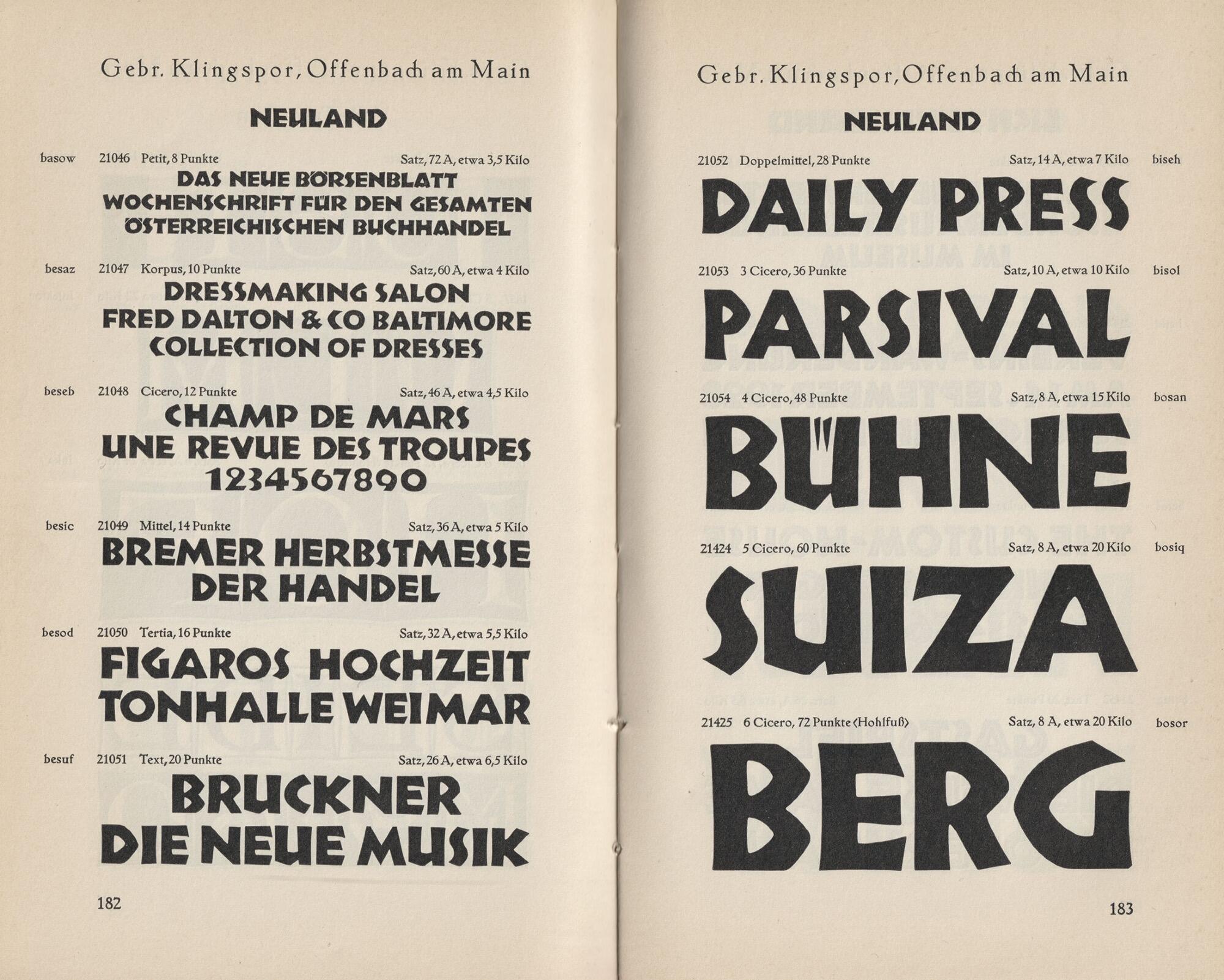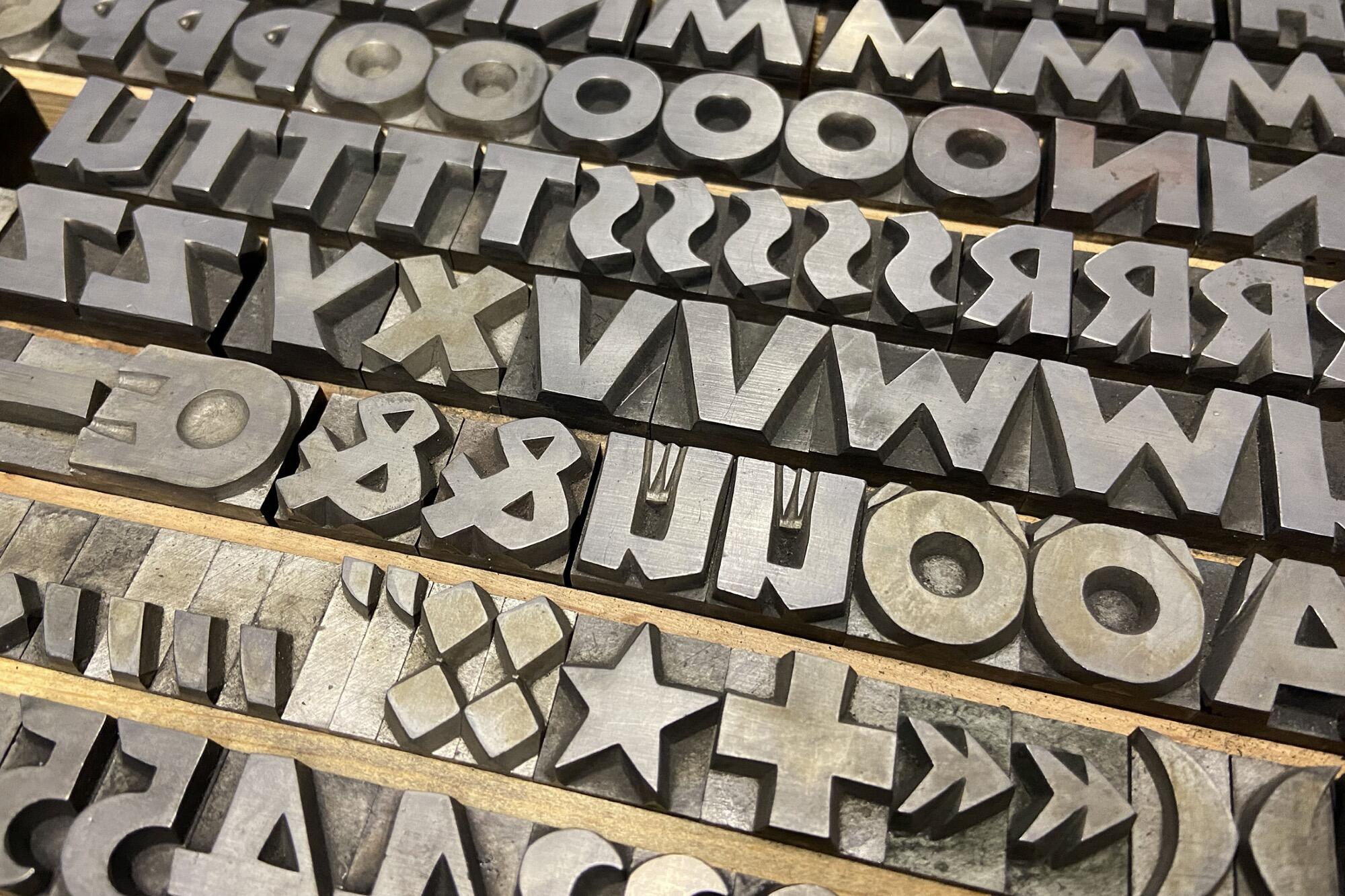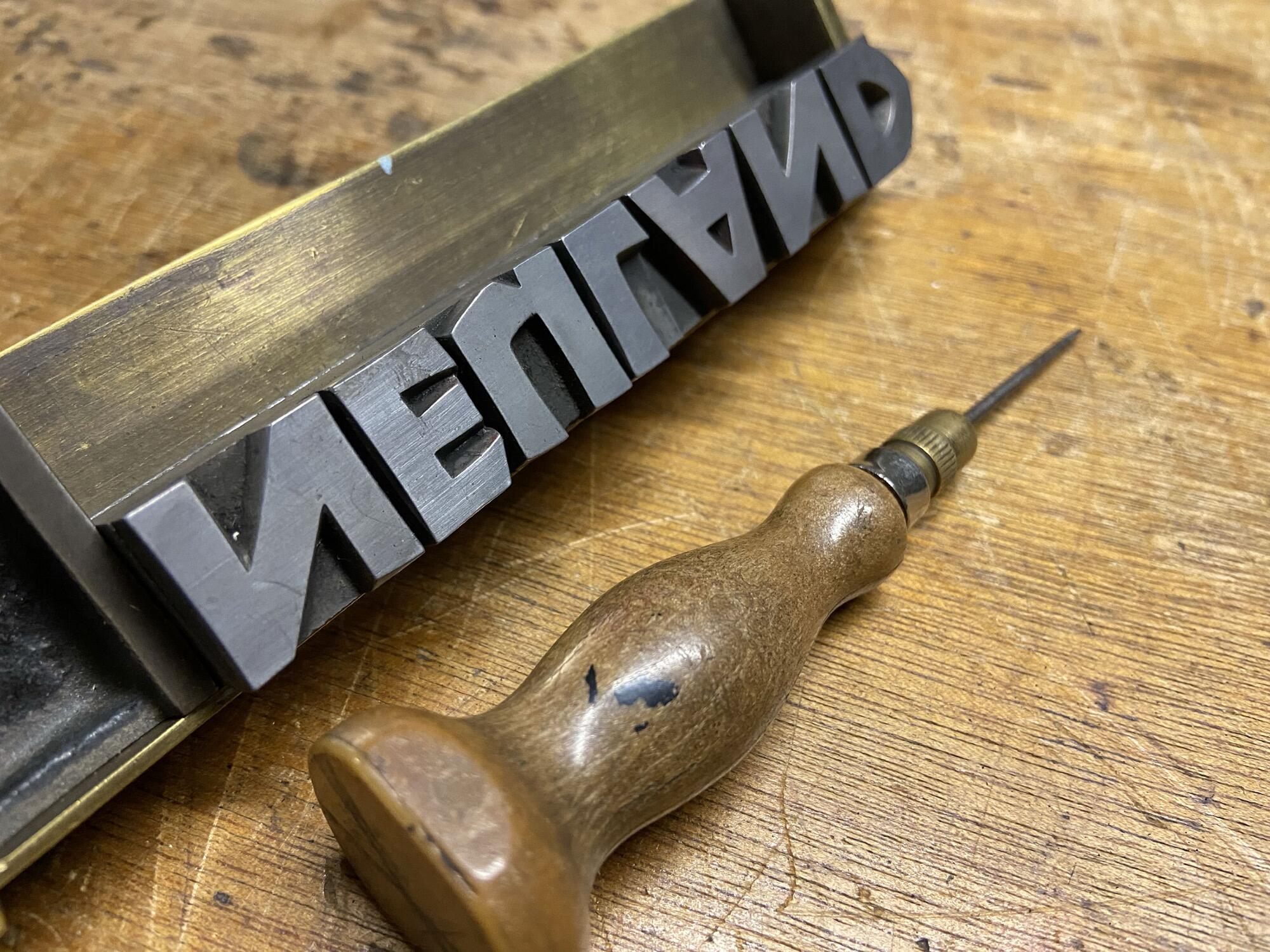
Die Versal-Schrift Neuland von Rudolf Koch erschien 1923 bei den Gebrüdern Klingspor in Offenbach. Obwohl eigentlich eher als Schreibmeister bekannt, versuchte sich Koch bei der Neuland selbst als Stempelschneider. Er wollte eine Schrift schaffen, die direkt aus dem Werkstoff entsteht und nicht durch Nachempfinden einer vorgegebenen Zeichnung.
»Daß ich eine Schrift selbst in Messing schneiden will, weißt Du wohl, es ist etwas ganz Unerhörtes und ich weiß, daß es für mich etwas Einschneidendes wird. Sechzehn Jahre habe ich gebraucht, um diesen Mut zu finden […]. Das meiste muß die Feile tun, dieses herrliche Werkzeug, in das die Nerven der Finger bis in die Spitze hineinlaufen. Ich will garnichts aufzeichnen, gleich loslegen. Es wird etwas Wildes gegen das, was bisher da war, aber doch soll es so exakt wie möglich werden. Jetzt wird es Leben in den Buchdruck kommen.« (Rudolf Koch in einem Brief an Ernst Kellner, 1922)
Koch schnitt nur einen Schriftgrad selbst. Seine Technik wurde jedoch auf die anderen Grade übertragen, sodass das Aussehen der Buchstaben absichtlich von Schriftgrad zu Schriftgrad unterschiedlich ausfiel.